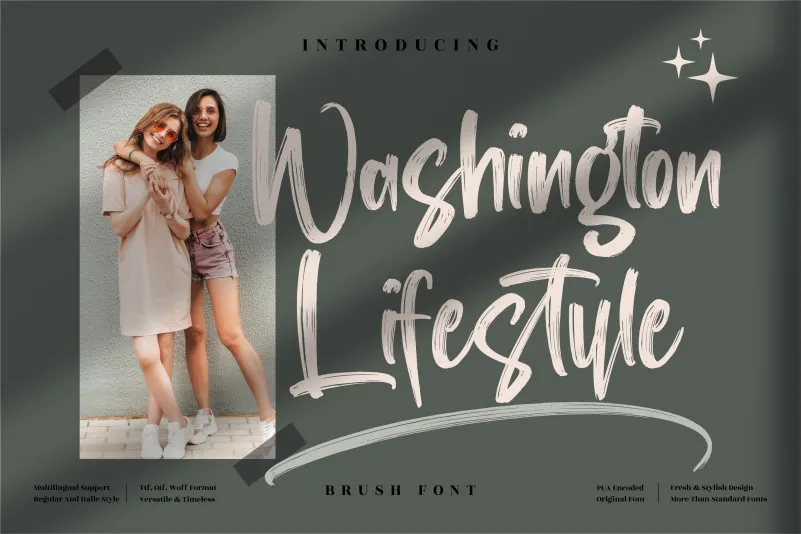
Esta é uma fonte script desenhada com um estilo aparentemente relaxado e bem-humorado, chamada Washington Lifestyle Font. Ela foi criada pelo designer perspectype e se destaca por sua elegância simples e deslizante. Este tipo de letra flui naturalmente, tornando-a atraente para uma variedade de projetos, desde as etiquetas no seu supermercado favorito até cartões de aniversário personalizados. Com um tom leve e agradável, Washington Lifestyle Font é perfeito tanto para criações menores quanto para elementos mais chamativos em suas propostas visuais. Seja você designer de logotipos ou criador de materiais publicitários, esta fonte terá o poder de dar seu trabalho aquele toque especial que torna a diferença entre um projeto simples e um verdadeiro lançamento. Não deixe sua biblioteca de fontes se manter sem este design único e atraente.